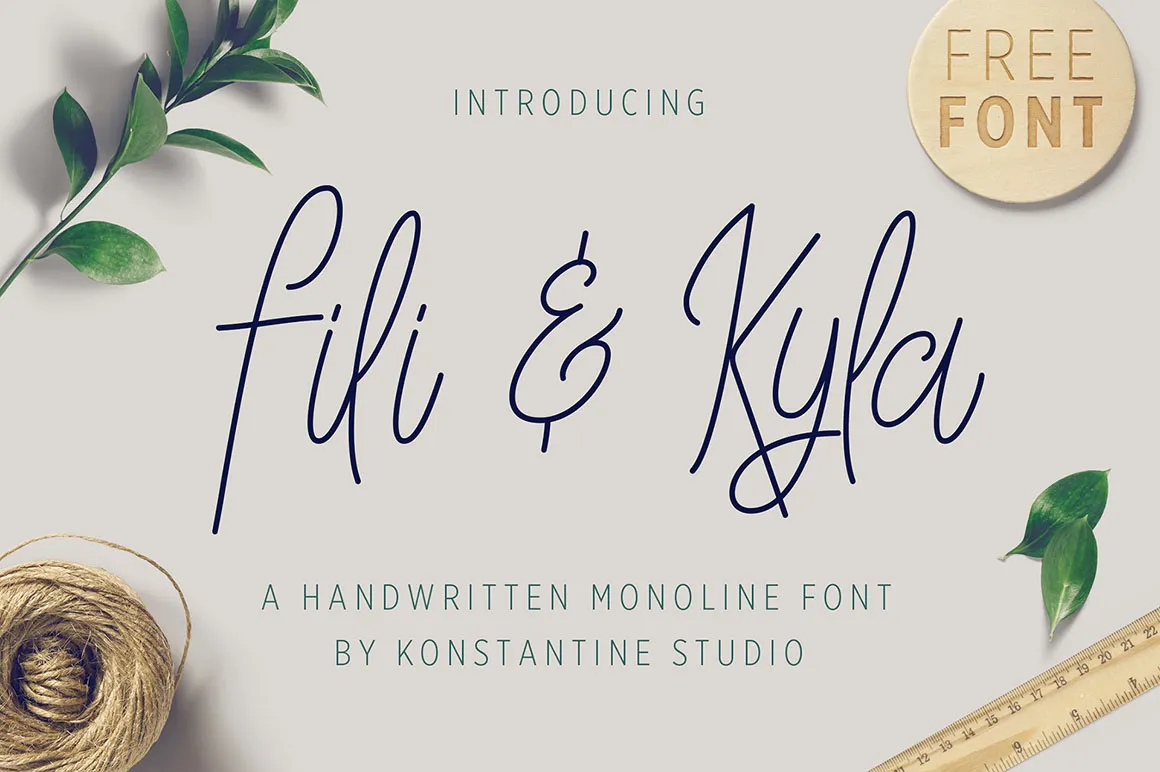
Fili & Kyla Script Font – Download Grátis
Olá amigos! Introduzimos a Fili & Kyla Script Font! Desenvolvida e compartilhada pela Konstantine Studio, a Fili & Kyla Script é uma fonte para assinatura ao estilo manuscrito. Esta fonte possui um charme elegante e encantador, com detalhes suaves (swashes). Ideal para diversas finalidades, desde logotipos e embalagens de produtos até convites de casamento, identidade visual, headlines, sinalização, rótulos, assinaturas pessoais, capas de livros, cartazes, citações e muito mais. Seja você um designer ou um amante das letras, certamente encontrará neste fonte uma maneira criativa e única de expressar sua personalidade através do texto. Não perca tempo, descubra Fili & Kyla Script Font!